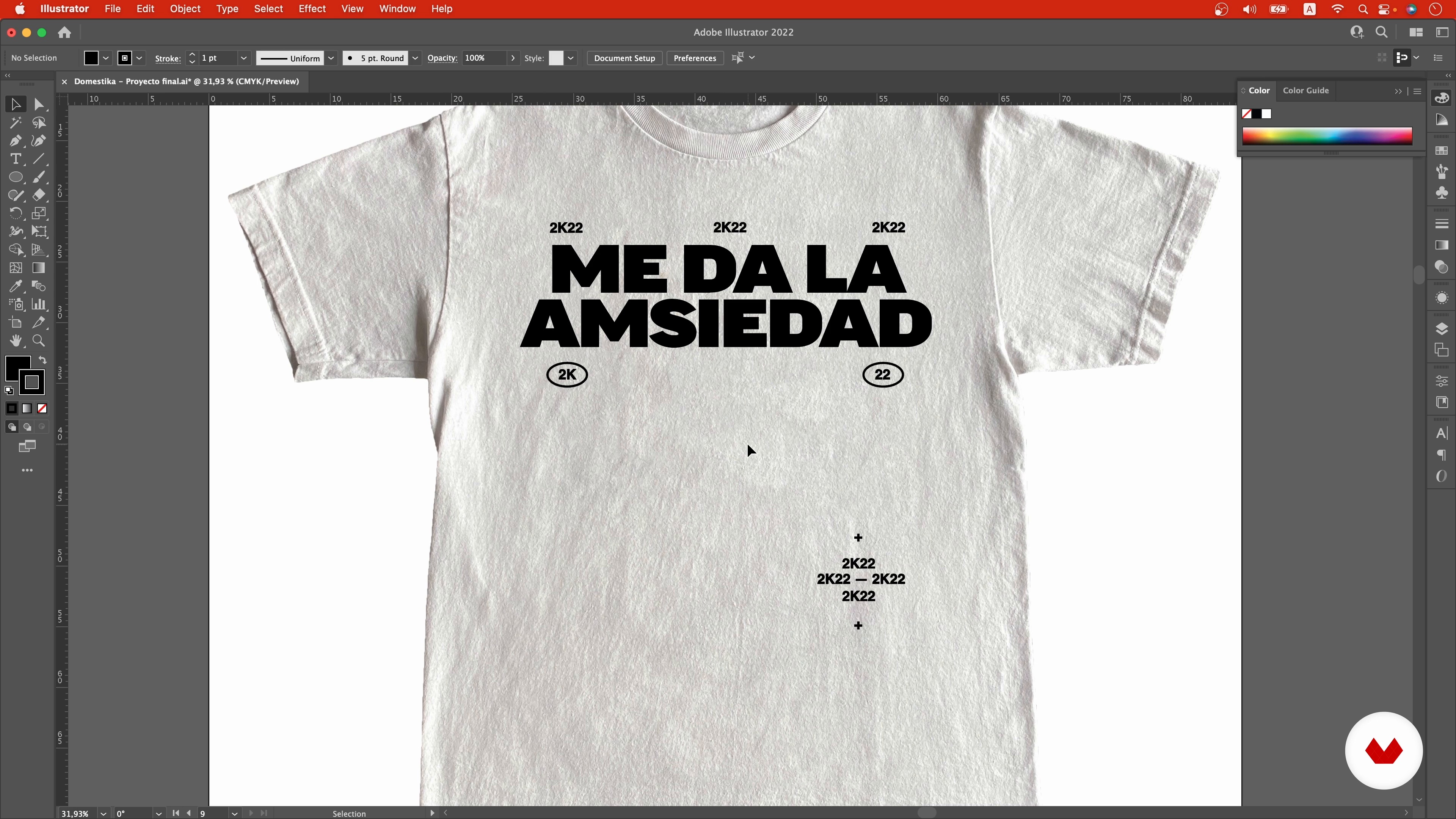
Création d'une typographie pour t-shirt
Disposition typographique 2
À propos de la leçon : Disposition typographique 2
“Petit à petit, je travaille dans Illustrator pour finaliser le schéma typographique de mon projet, en ajustant chaque détail.”
Dans cette leçon, Joaquín Lluis aborde le sujet : Disposition typographique 2, qui fait partie du cours Domestika en ligne : Création d'une typographie pour t-shirt. Découvrez les secrets de la création de t-shirts et exprimez vos idées créatives..
“Eh bien, auparavant, nous cherchions comment générer ce diagramme typographique et nous l'avons fait cette première approximation ou schéma simple en utilisant une police assez par défaut que nous avons dans Illustrator, qui est le Miria Pro, mais maintenant nous allons faire un sélection typographique, au moins de la première partie de ce titre principal. Pour cela, ce que j'ai fait, c'est un petit dessin, un petit dessin de l'image, un petit dessin de ce titre principal. Pour cela, j'ai dupliqué ce plan de travail plusieurs fois afin que nous puissions faire des sélections différentes. Av...”